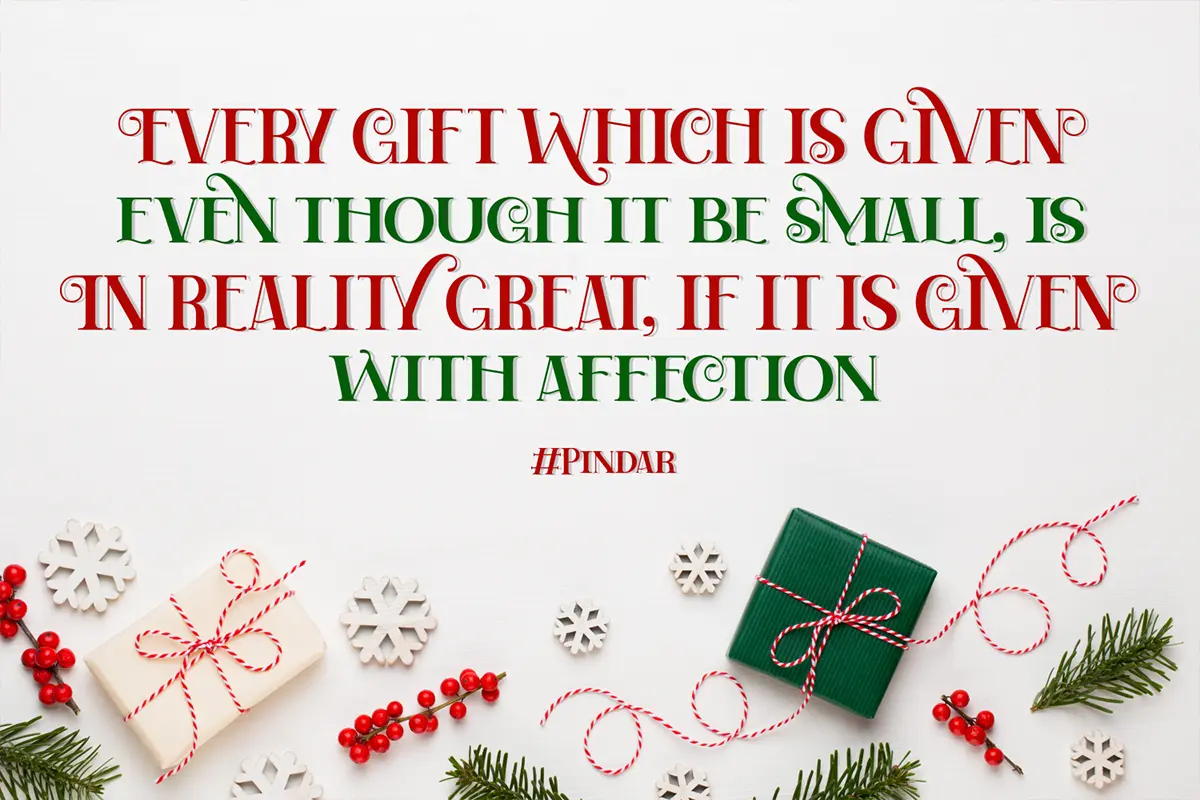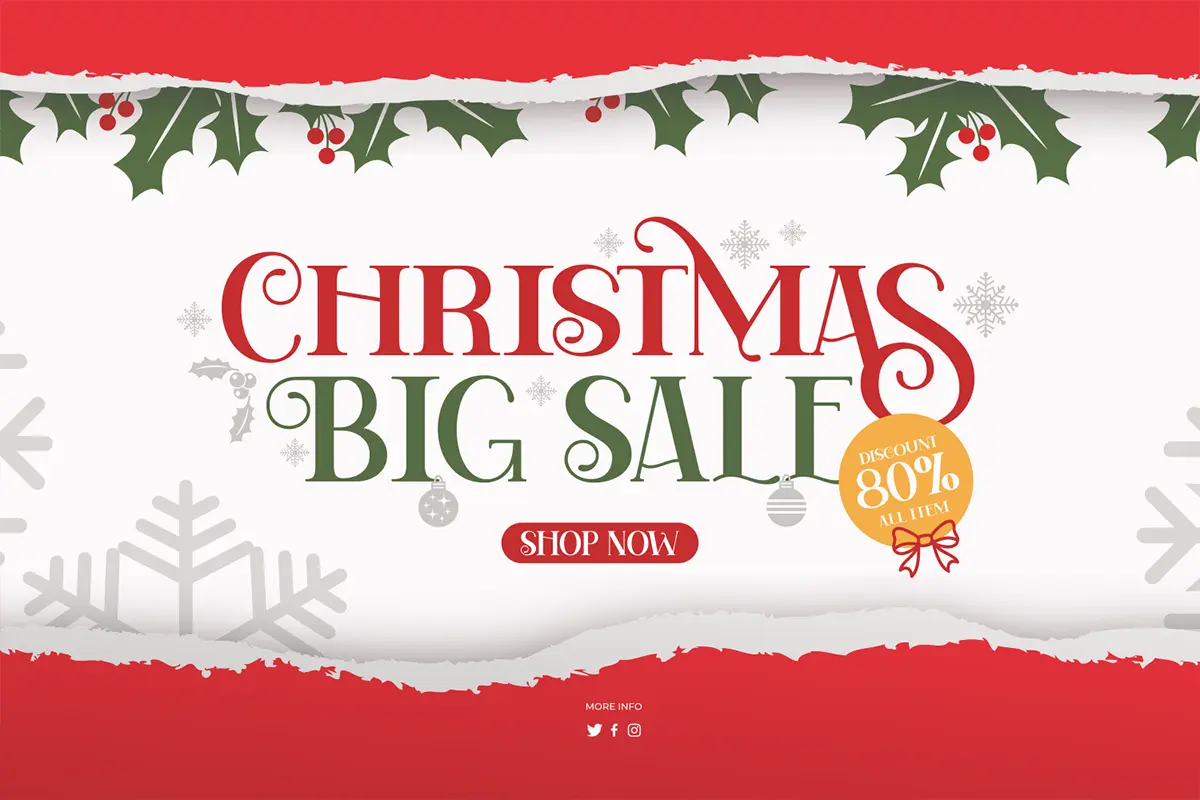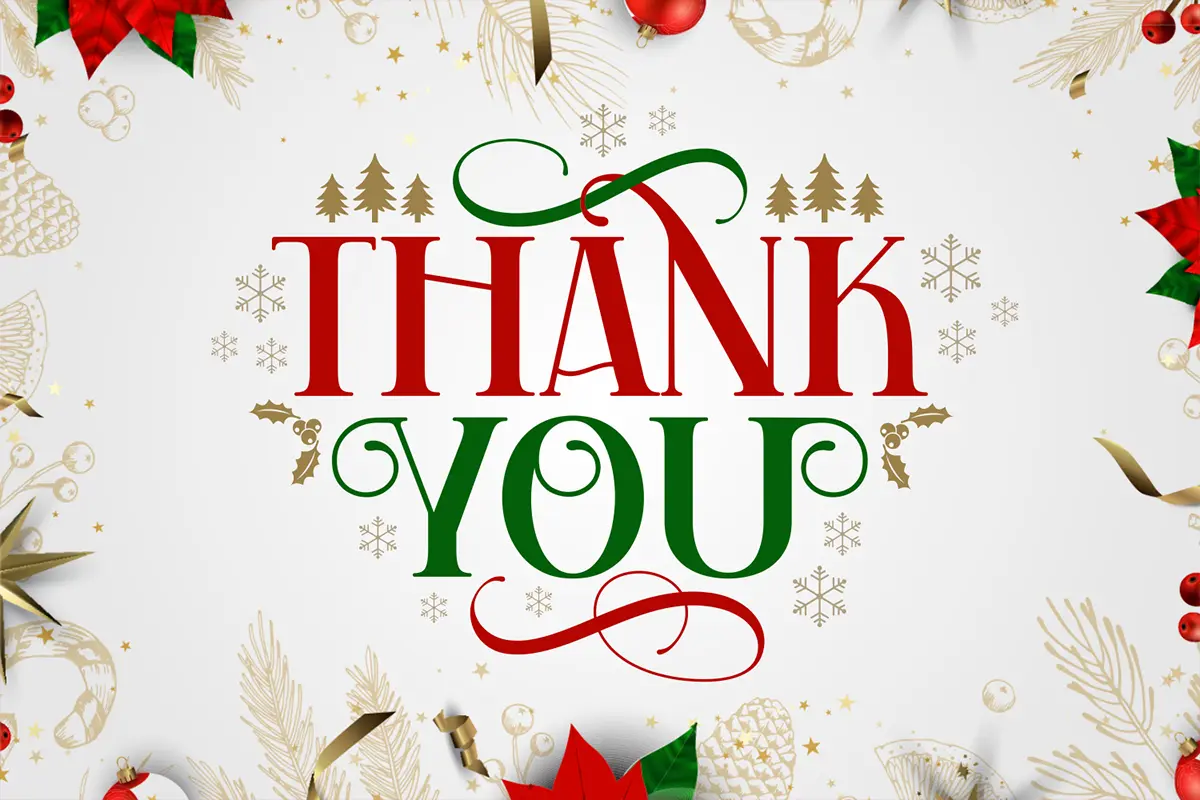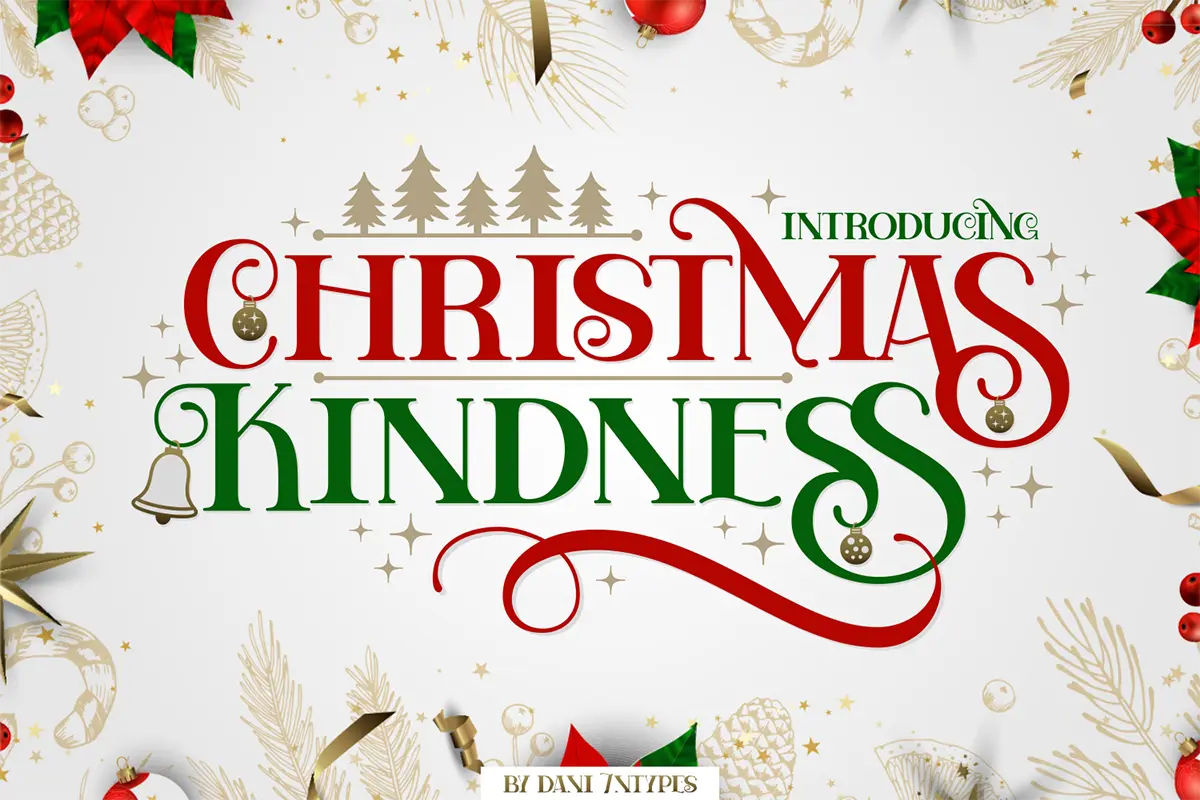
فونت کریسمس Christmas Kindness
Christmas Kindness یک فونت نمایشی (Display Font) با حالوهوای شاد، دوستانه و مناسب طراحیهای کریسمسی و زمستانی است. این فونت برای ساخت پوستر، کارت تبریک، بستهبندی، تیترهای گرافیکی، استیکر، طراحی شبکههای اجتماعی و هر پروژهای که نیاز به حس گرم و جشنگونه دارد، انتخابی عالی است.
- فونت نمایشی (Display Type Font)
- مناسب برای طراحیهای کریسمسی، زمستانی و فصلی
- قابل استفاده در پوستر، کارت تبریک، بستهبندی، شبکههای اجتماعی و تبلیغات
- سبک دوستانه، شاد و جذاب